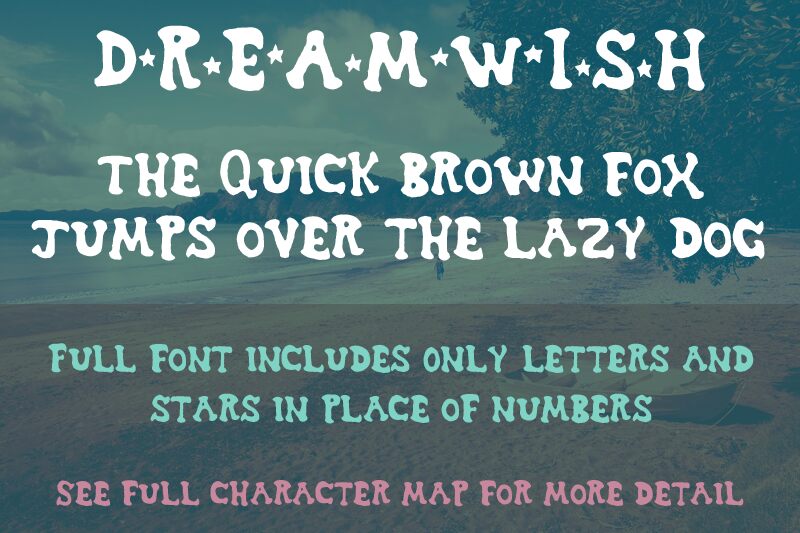
Dreamwish, ursprünglich Ende 2002 veröffentlicht, ist eine lebhafte, verspielte und wie aus einem Cartoon wirkende Schrift mit traumhaftem Charakter. Sie ist so konzipiert, dass sie zusammen mit den Sternsymbolen verwendet werden kann, die sich bei den Ziffern befinden. Da es sich nicht um einen vollständigen Zeichensatz handelt, ist die Schrift kostenlos. Viel Spaß damit!
Sie enthält Groß- und Kleinbuchstaben, Zahlen und Satzzeichen.
Dreamwish